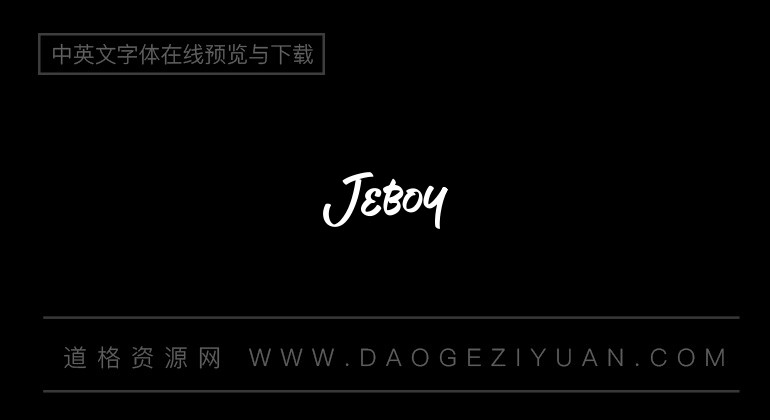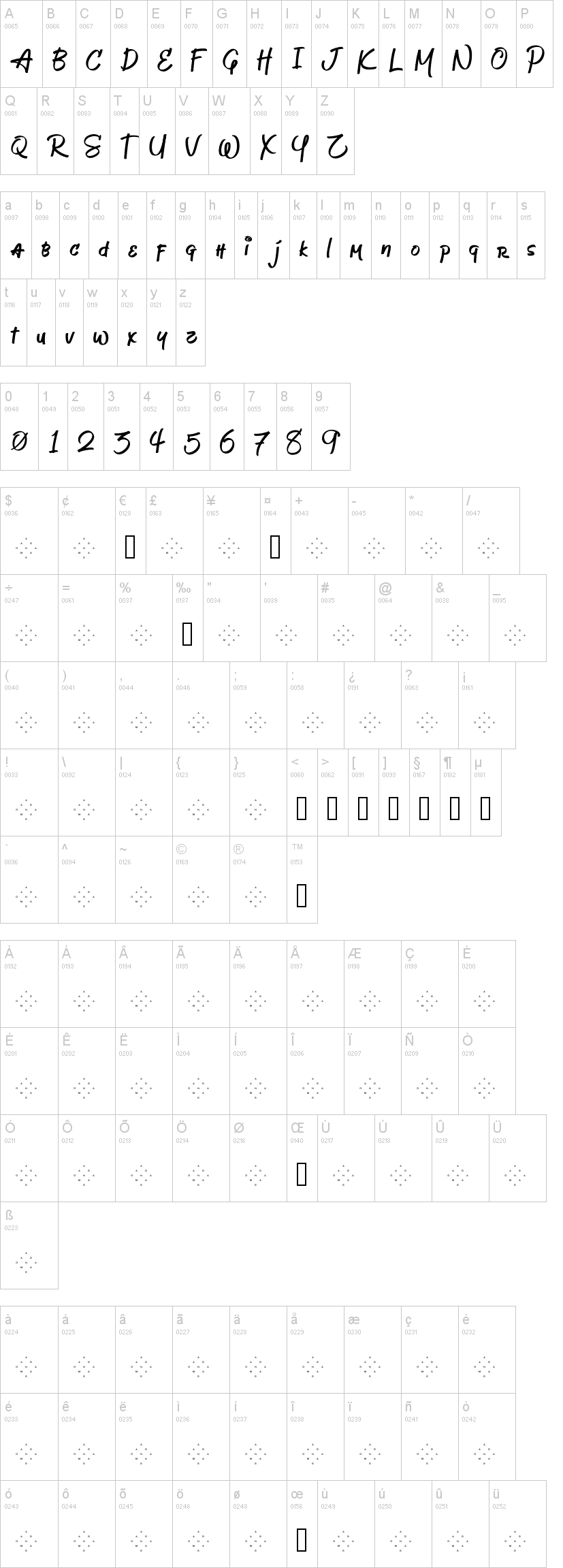
Jeboy
? Jeboy字体是一款极具个性的手写风格字体,它有着极具个性的外观,能够很好地把表达者的情感融入到字体中。它拥有清晰的线条,柔和的笔触,以及清晰的字形,可以很好地表达出文字的意思。它具有极高的可读性,可以轻松地将文字展示出来,而且它的设计风格也很有趣,可以给文字带来活力和个性。
Jeboy是一款非常不错的手写艺术字体,具有很好的视觉感,适合于文化类的宣传设计、商业类品牌的广告和产品包装设计以及个性化文字排版等较多场景。